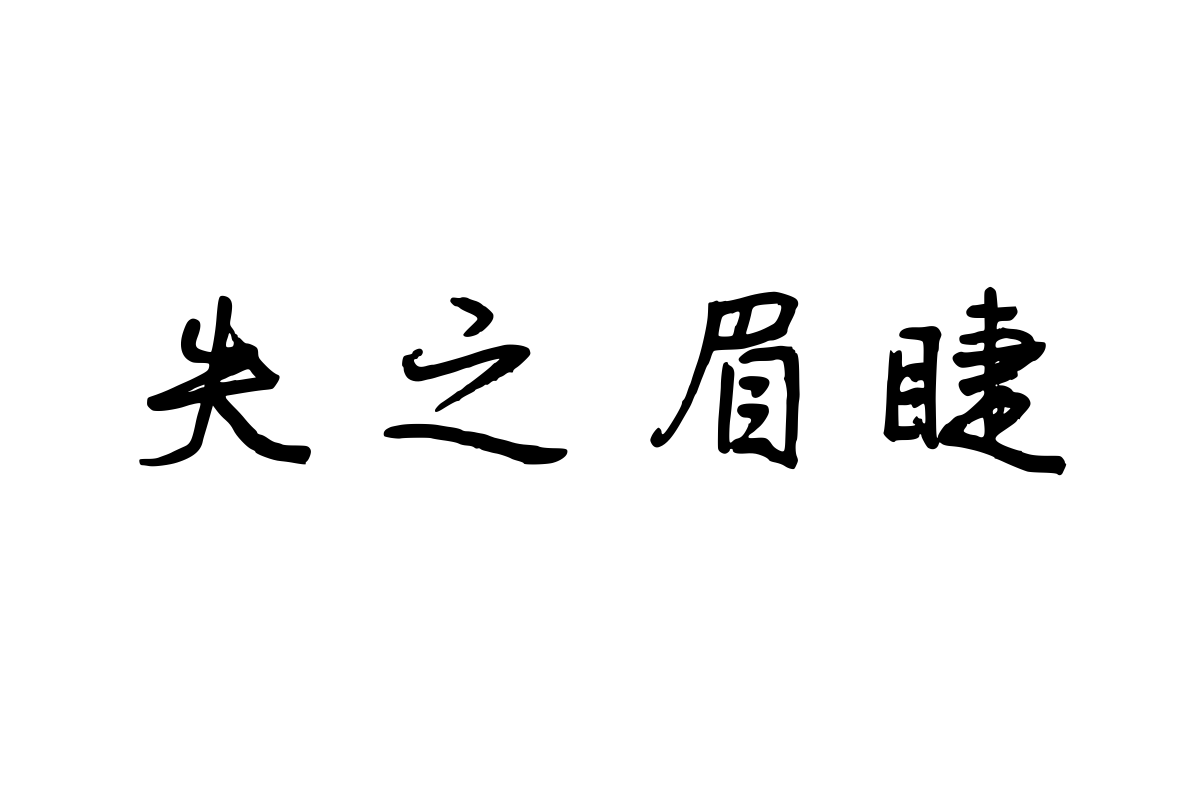
兰米飘逸行楷简繁体版是一款兼具美观和实用性的字体。它由著名书法家兰米创作,融合了行楷与草书的元素,形成了独特的风格。这款字体线条流畅,结构严谨,既有行楷的规整感,又不失草书的自由度。它的笔画粗细适中,既有力度又有美感,适合用于各种书写和设计场景。无论是在印刷品还是电子屏幕上,兰米飘逸行楷简繁体都能展现出其独特的魅力。